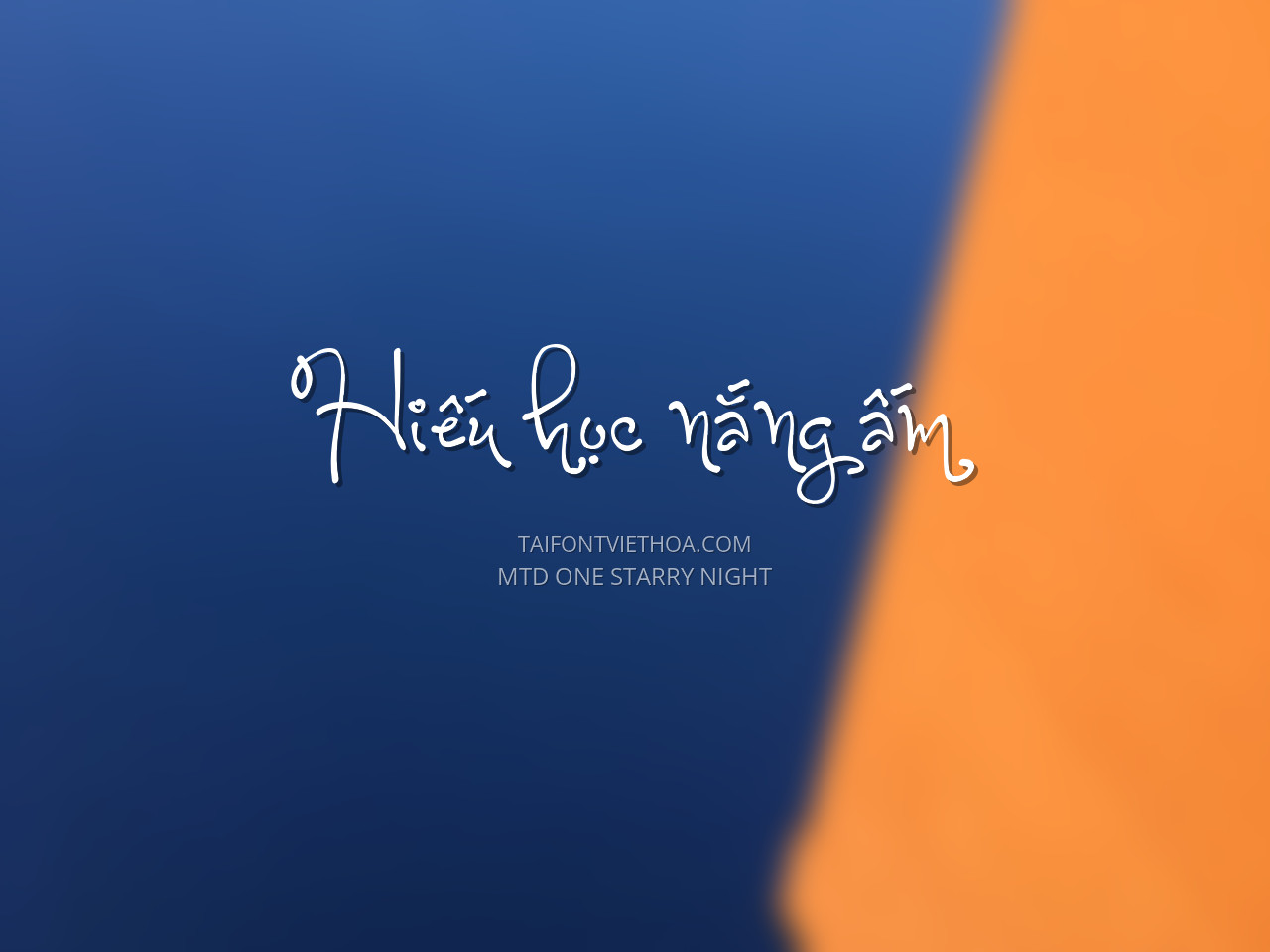
Font việt hóa MTD One Starry Night
Tác giả Font: Brittney Murphy
Giới thiệu về font One Starry Night
One Starry Night là một font script nghệ thuật mang cảm hứng cổ tích, được thiết kế bởi Misti’s Fonts và Việt hóa bởi Motokiwo Type (MTD). Font mang vẻ huyền ảo và bay bổng, gợi nhắc đến những câu chuyện cổ tích dưới bầu trời đầy sao, đúng như tên gọi. Với những đường nét mềm mại, uốn lượn và độ nghiêng duyên dáng, One Starry Night phù hợp hoàn hảo với các thiết kế cần truyền tải sự lãng mạn, mơ mộng hoặc phép màu. Phiên bản Việt hóa hỗ trợ đầy đủ tiếng Việt cùng hơn 60 ngôn ngữ khác, đảm bảo khả năng ứng dụng rộng rãi trong nhiều nền tảng sáng tạo.
Đặc điểm thiết kế và ứng dụng của font One Starry Night
Font có cấu trúc chữ viết tay mềm mại, nhẹ nhàng với độ nhún (bounce) nhẹ giữa các chữ cái, tạo hiệu ứng chuyển động uyển chuyển và bắt mắt. Các swashes và ligatures được tinh chỉnh công phu giúp font phù hợp cho tiêu đề lớn, chữ ký thương hiệu, hoặc typography cảm xúc.
Ứng dụng lý tưởng của One Starry Night gồm: thiết kế thiệp cưới cổ tích, bìa sách thiếu nhi, bao bì sản phẩm handmade, tiêu đề blog sáng tạo, hoặc nội dung truyền thông hướng đến cảm xúc nghệ thuật. Ngành nghề phù hợp: cưới hỏi, làm đẹp, thời trang nữ, thiết kế đồ thủ công, truyền thông nghệ thuật và quảng cáo sáng tạo cảm xúc.